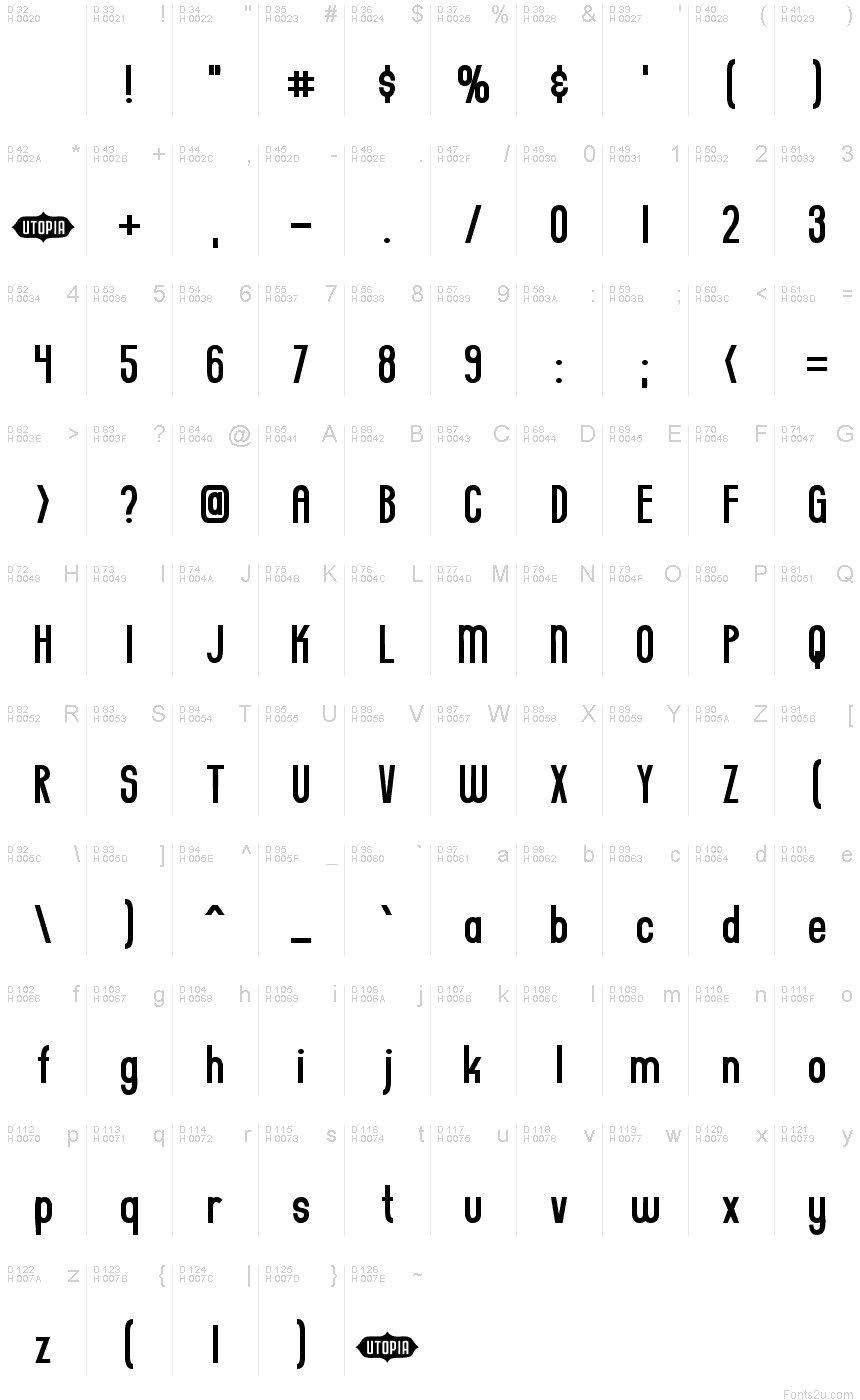
Everyday Formula Gaunt
Everyday Formula Gaunt od Utopiafonts to darmowy, wąski krój bezszeryfowy, który zamienia ciasne układy w wyraziste i przejrzyste projekty. Jego wysokie, smukłe litery o zdecydowanych, kwadratowych łukach pozwalają zmieścić dużo treści w wąskich kolumnach, dzięki czemu możesz przekazać więcej bez wrażenia przeładowania. Kreski są solidne i wyraziste, co nadaje nagłówkom pewny, konkretny charakter nawet w małych rozmiarach.
Używając Everyday Formula Gaunt, możesz zagęścić układ okładek magazynów, banerów reklamowych, etykiet UI, plakatów i opakowań, nie tracąc przy tym na czytelności. Ten darmowy font świetnie sprawdza się w odważnych tytułach, paskach bocznych, napisach na grzbietach książek i wszędzie tam, gdzie przestrzeń w pionie jest ograniczona, a liczy się siła przekazu. Spróbuj zestawić go z szerszym, łagodniejszym krojem bezszeryfowym w tekście głównym, aby zrównoważyć jego zwartą i napiętą energię.